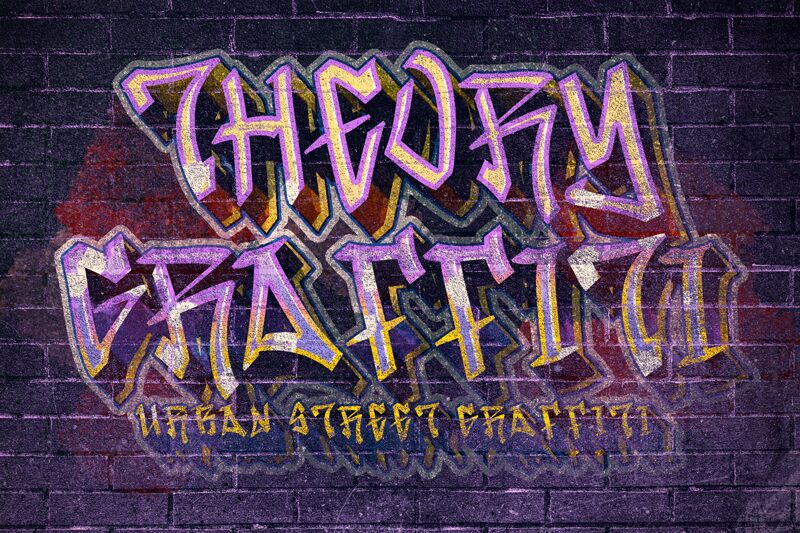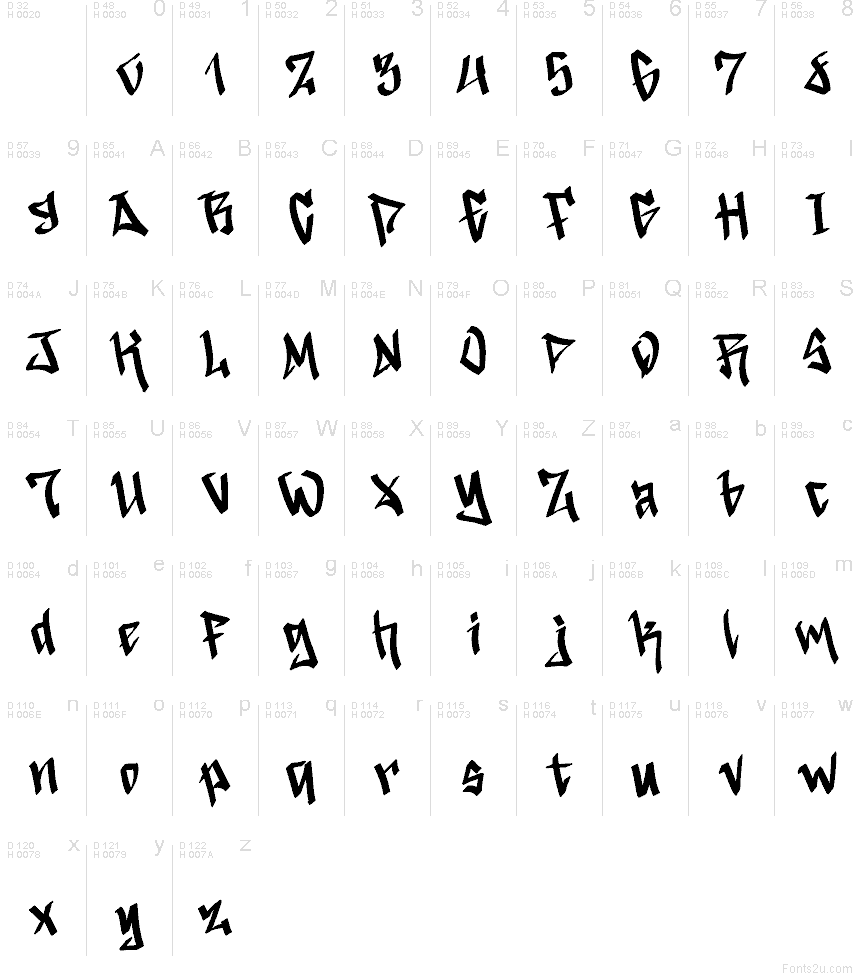
Theory Graffiti ist eine kostenlose Graffiti-Schriftart mit scharfen, kantigen Strichen und kompakten Verbindungen, die den Buchstaben einen dynamischen, tag-artigen Rhythmus verleihen. Die Formen kombinieren spitze Schnitte mit einem flüssigen, handgezeichneten Stil, sodass das Schriftbild rau und authentisch wirkt, ohne dabei an Struktur zu verlieren.
Theory Graffiti eignet sich hervorragend für Streetwear-Logos, Plakatüberschriften, Musik-Artworks, Skate-Grafiken und Branding im Mural-Stil. Die kantigen Formen und improvisierten Striche sind perfekt für Projekte, die einen rohen, handgeschriebenen Look benötigen – besonders dann, wenn das Design eine urbane Note statt förmlicher Typografie erfordert.